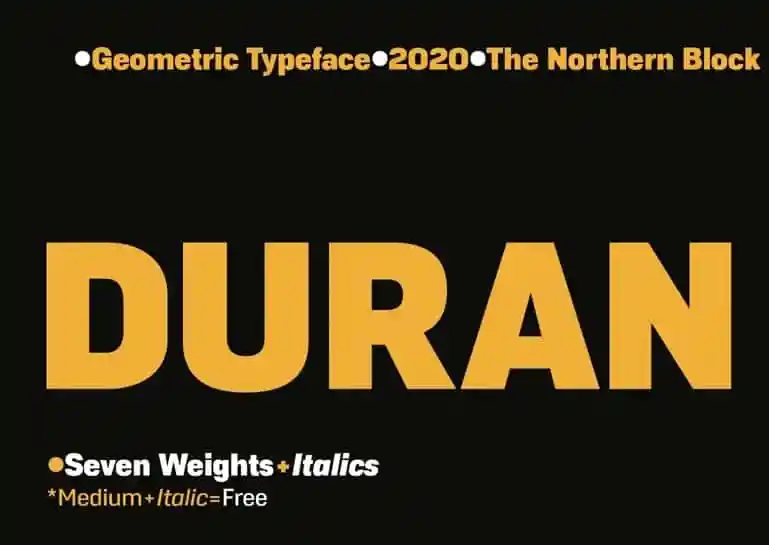
A Duran Sans Serif é uma nova tipografia neo-grotesca baseada em formas geométricas que captura a essência de um tipo moderno e amigável, mas com forte atitude. Desenhada pelo The Northern Block, esta fonte inspira-se nos traços técnicos contemporâneos, apresentando uma construção simples e prática que oferece grande utilidade tanto em grandes formatos quanto no texto corpo. Seu formato lateral compacto ajuda a economizar espaço em várias páginas, tornando-a perfeita para aplicações modernas de todos os tipos. A Duran Sans Serif é um recurso visual elegante que se destaca sem perder a simplicidade e robustez do seu design.